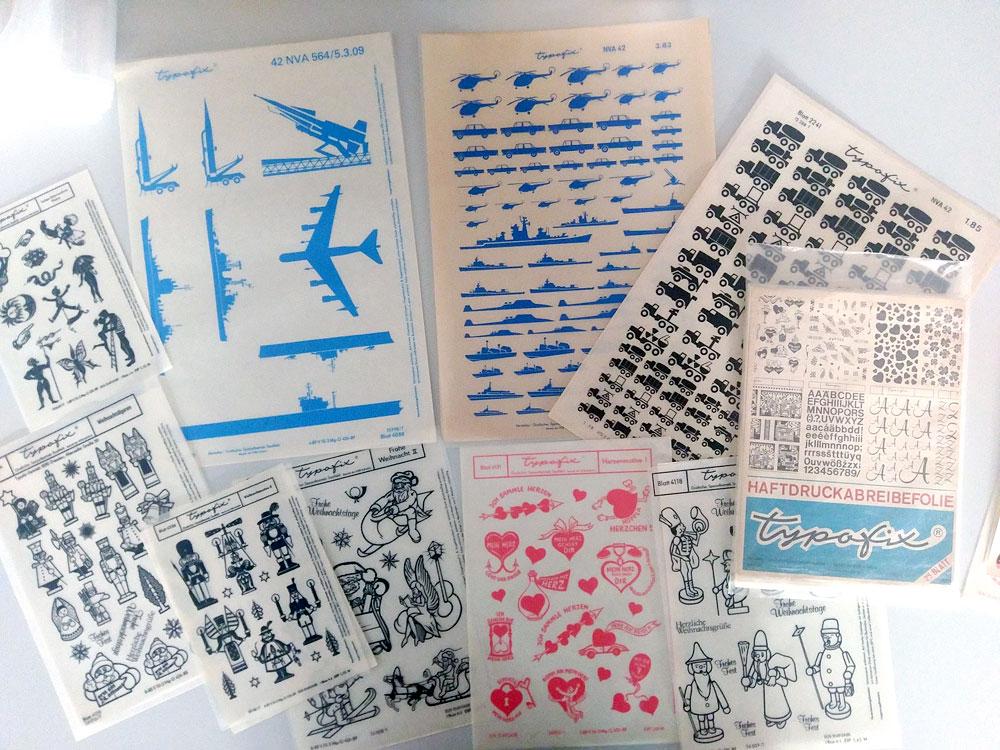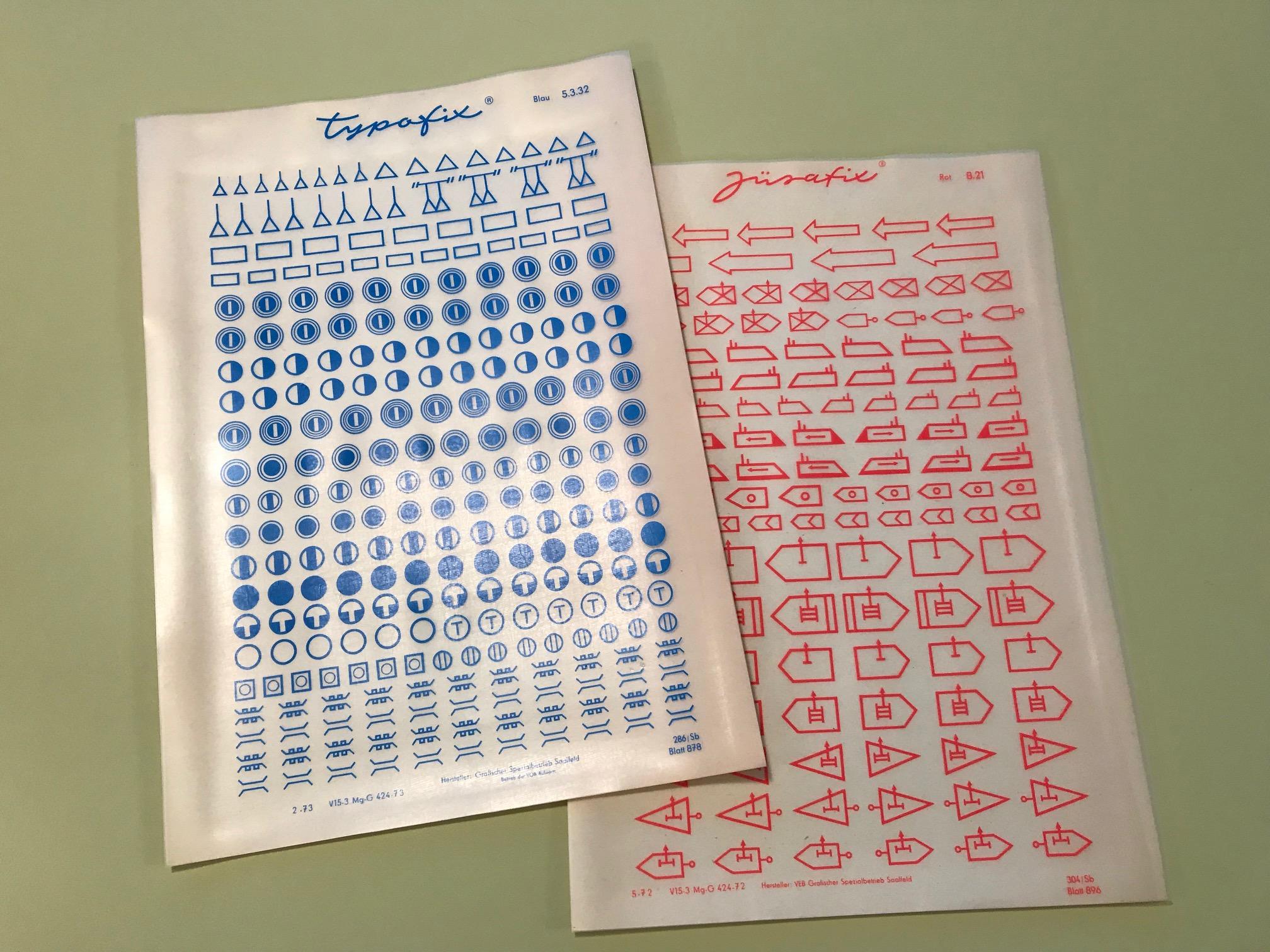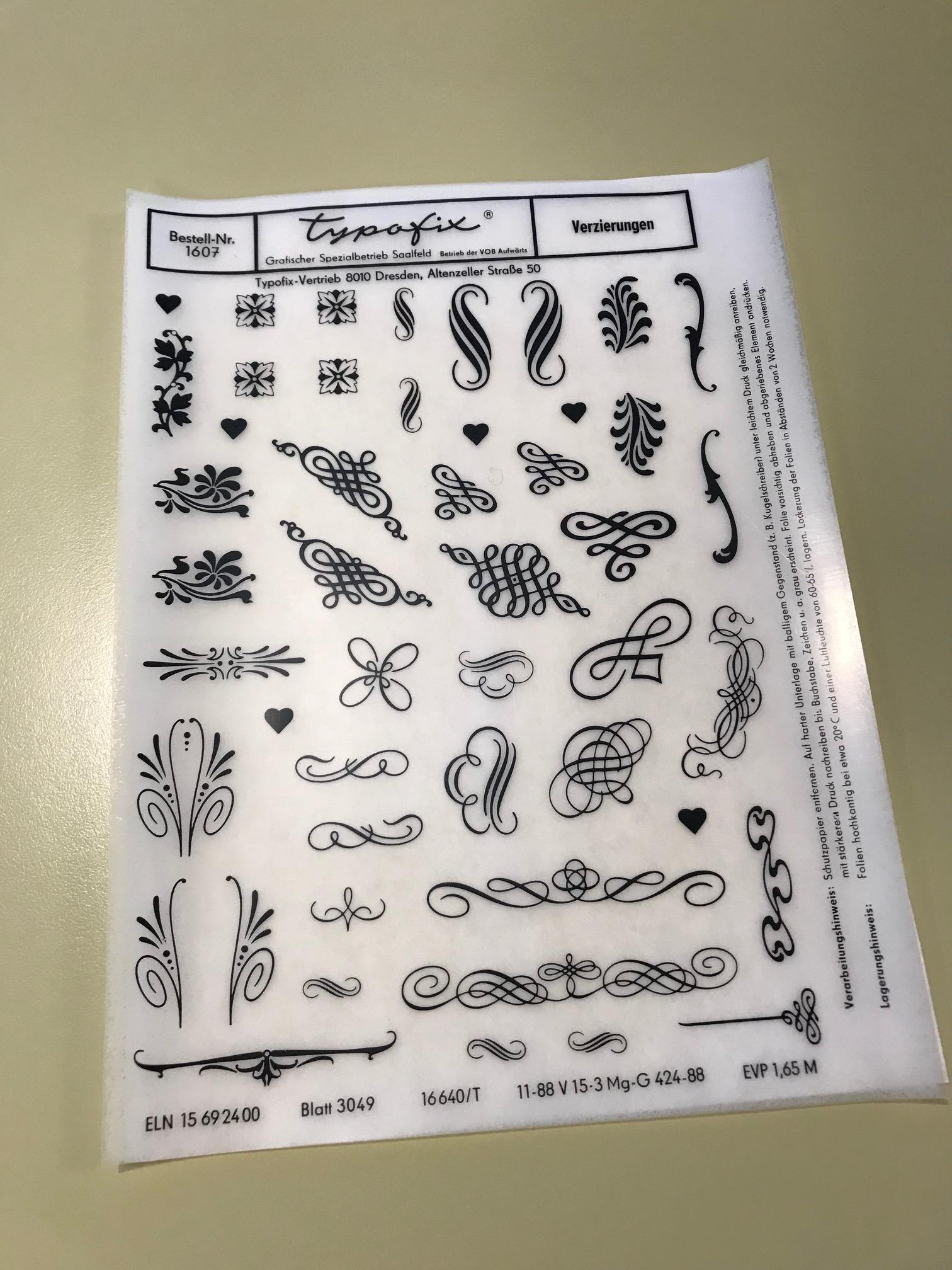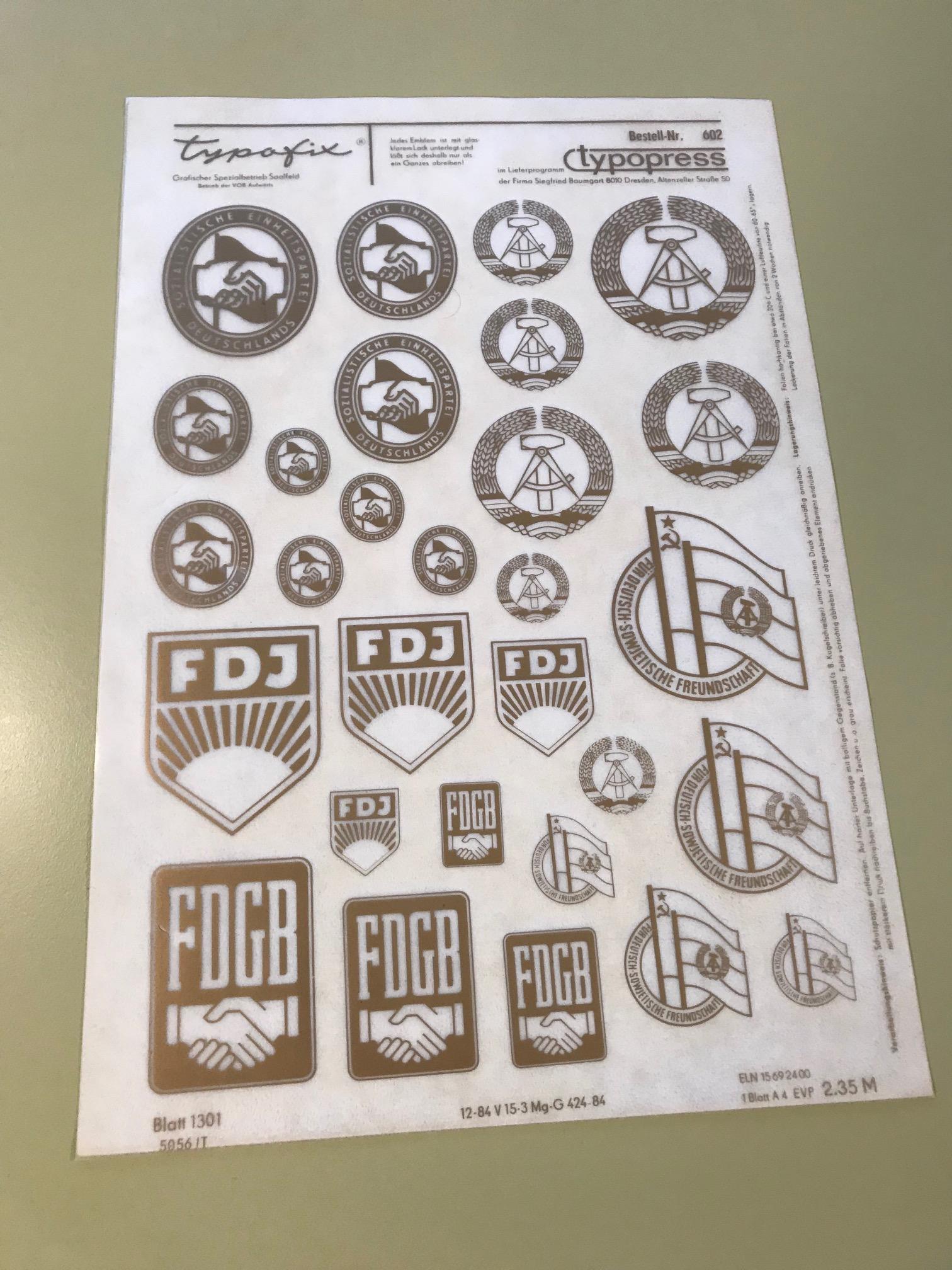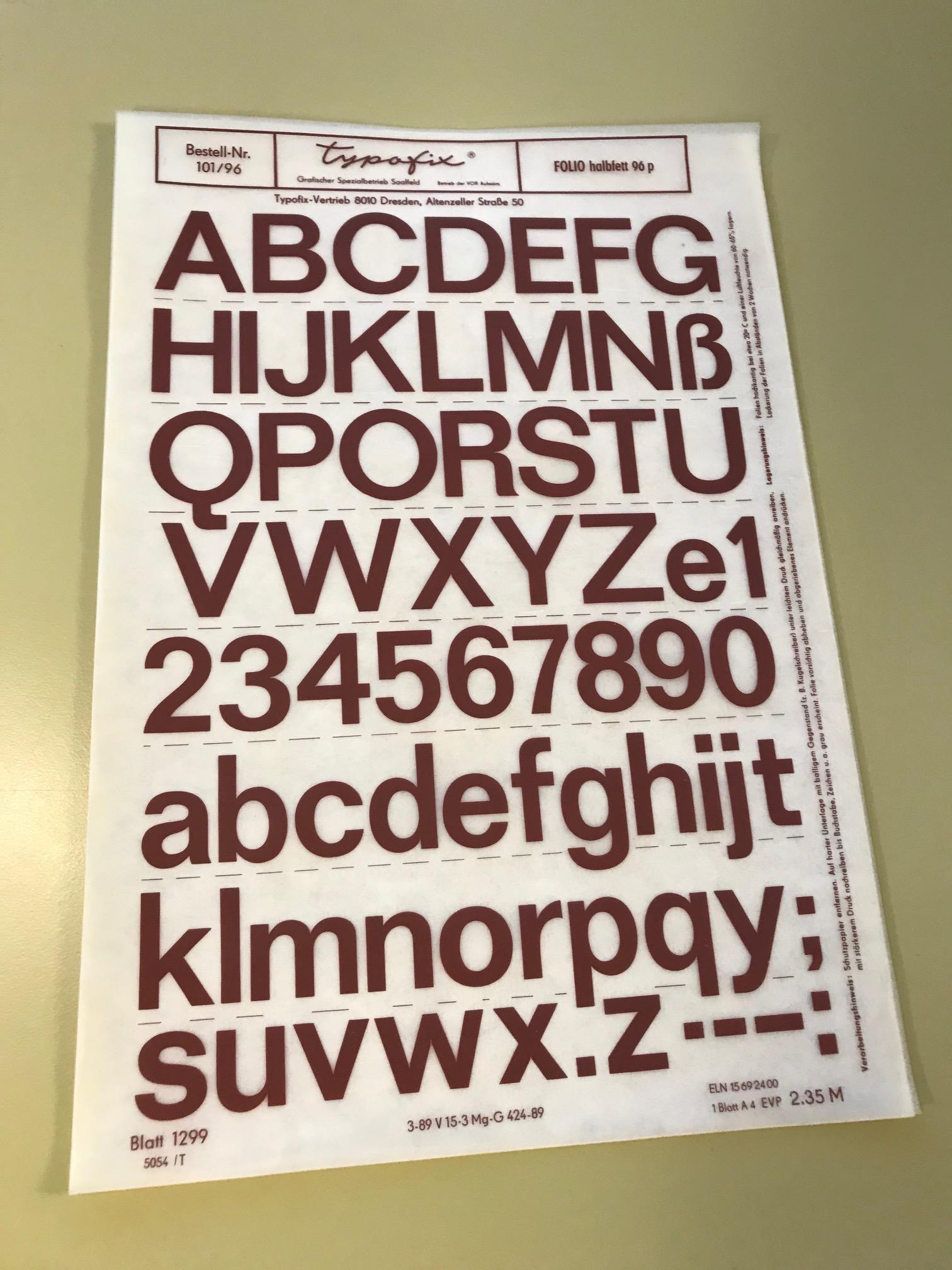
Typofix, Abifol, Jürafix, typopress
Die Abreibefolien gab es in den Namen Typofix, Abifol, Jürafix.
Ein Programm namens "typopress" mit Vertrieb in Dresden.
Leider gibt das Internet wenig Auskunft darüber.
Kann jemand über Hintergründe der unterschiedlichen Namensgebung, Herstellung, Produkte und Geschichte berichten?
habe soeben mal auf meinen alten Bögen nachgesehen, eventuell hilft Dir das ja weiter:
Typofix, Hersteller Grafischer Spezialbetrieb Saalfeld, Betrieb der VOB Aufwärts
Vertrieb: typofix-Vertrieb 8010 Dresden, Altenzeller Straße 50
Typopress war das Lieferprogramm der Firma Siegfried Baumgart 8010, Altenzeller Straße 50
Also vermutlich der typofix-Vertrieb
Meine Jürafix Bögen sind von 1972, allerdings alle schon mit VEB Grafischer Spezialbetrieb Saalfeld beschriftet.
interessantes Q hat die Folio – ist mir nie so aufgefallen :cheer:
Zur Frage ob es einen Katalog gab:
Würde mich auch interessieren, eventuell sollte man hier mal einen damaligen Schreibwarenhändler befragen wie diese früher bestellt/ausgesucht wurden. Kam da ein Vertriebler mit 'ner großen Mappe in den Laden oder gab es einen Katalog (was ich irgendwie bezweifle)? Das Programm der typofix-Bögen war ja riesig und reichte von kitschigen Herzchen, Buchstaben, Weihnachtsmännern und Osterhasen bis zu technischen Symbolen zur Leiterplattenbeschriftung. Kann mich auch an unzählige Scherenschnittmotive von Engeln etc. erinnern. Mich würde auch die Entstehung der Bögen interessieren, vorallem die Symbole (gerade das NVA-Zeugs) – hat die jemand extra dafür gezeichnet?
… eventuell sollte man hier mal einen damaligen Schreibwarenhändler befragen wie diese früher bestellt/ausgesucht wurden …
Ausgesucht und bestellt? Man bekam was gerade da war!
Mal Herzen, mal Engelchen und mal Langstreckenbomber ... :cheer:
Mich würde auch die Entstehung der Bögen interessieren, vorallem die Symbole (gerade das NVA-Zeugs) – hat die jemand extra dafür gezeichnet?
Ich habe auch etliche Bögen mit Typo auf denen oben groß NVA drauf steht. Eventuell kam die zivile Nutzung erst nach der militärischen ...